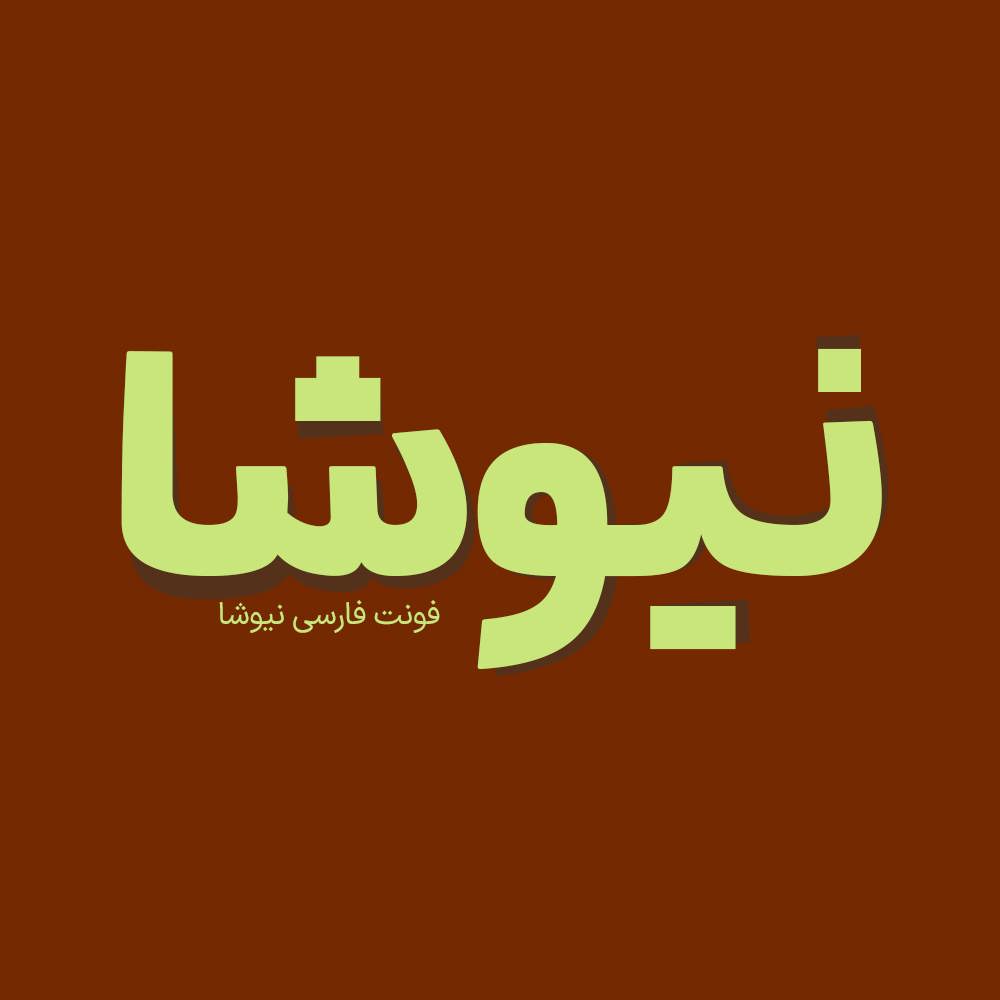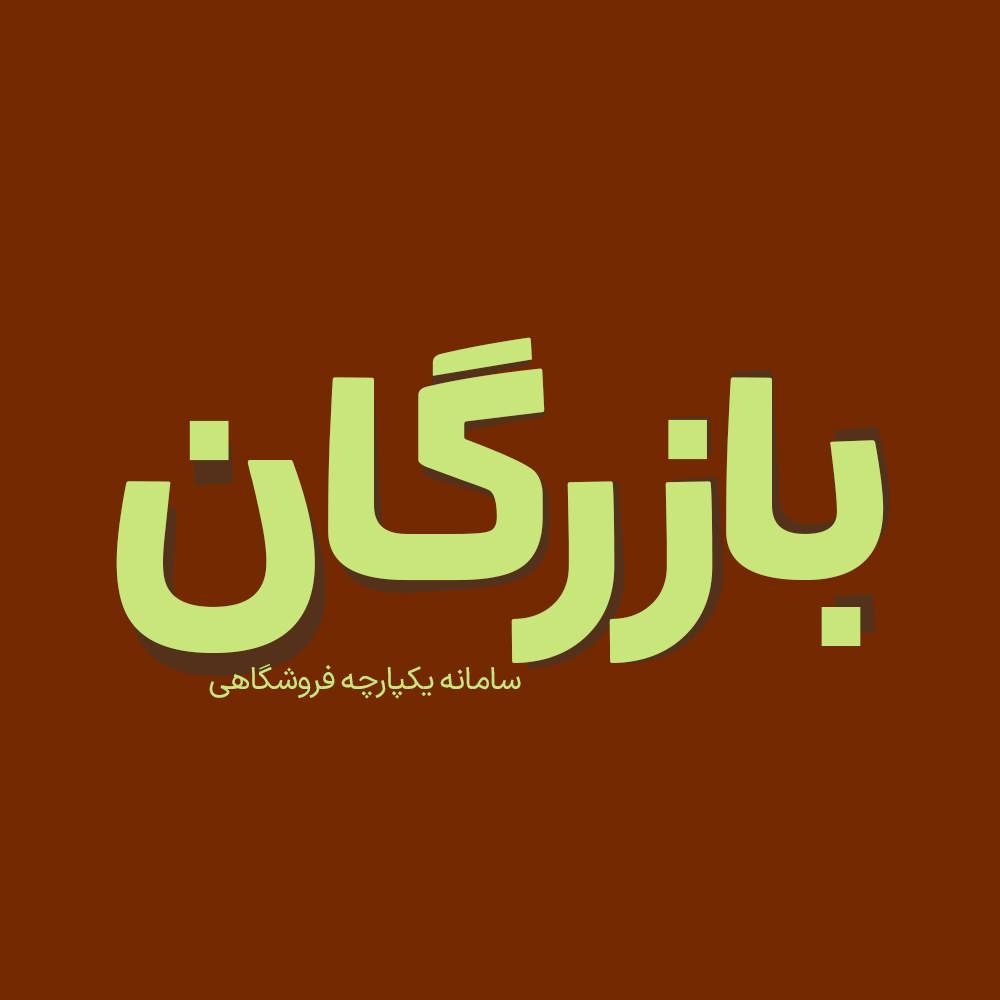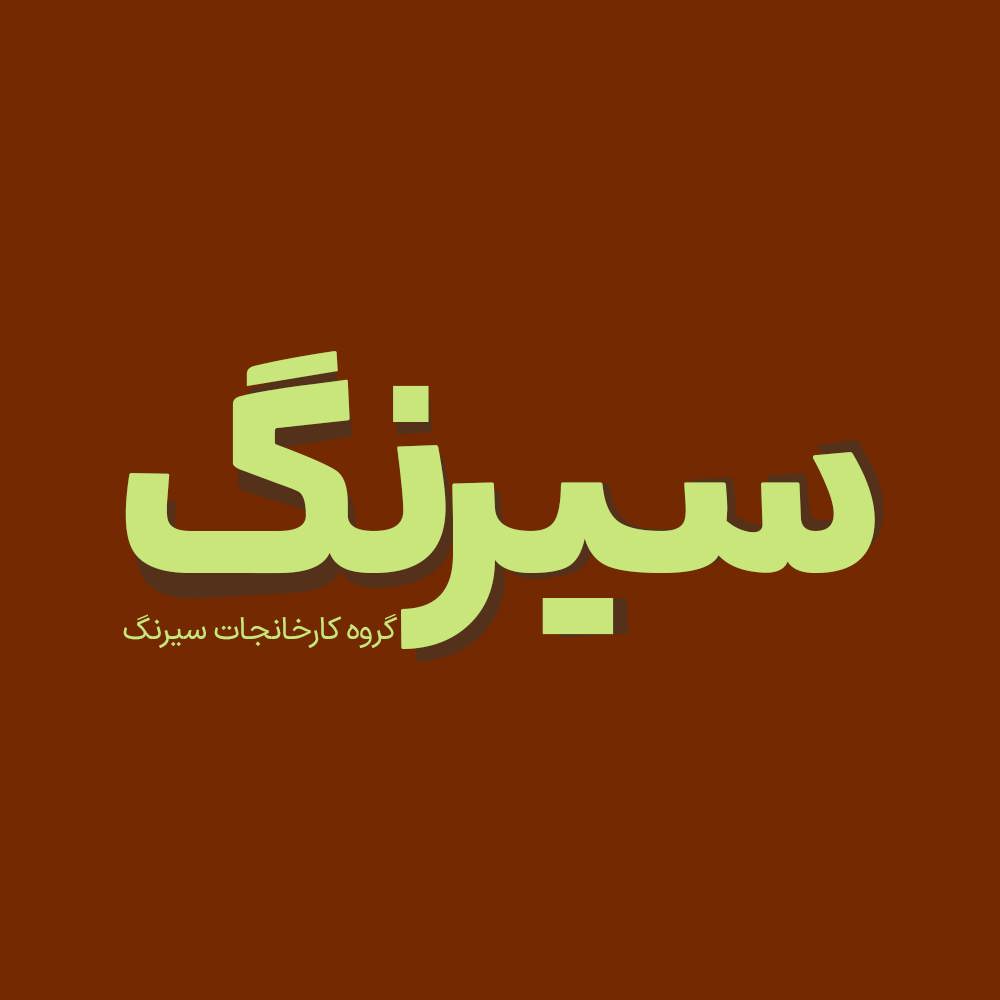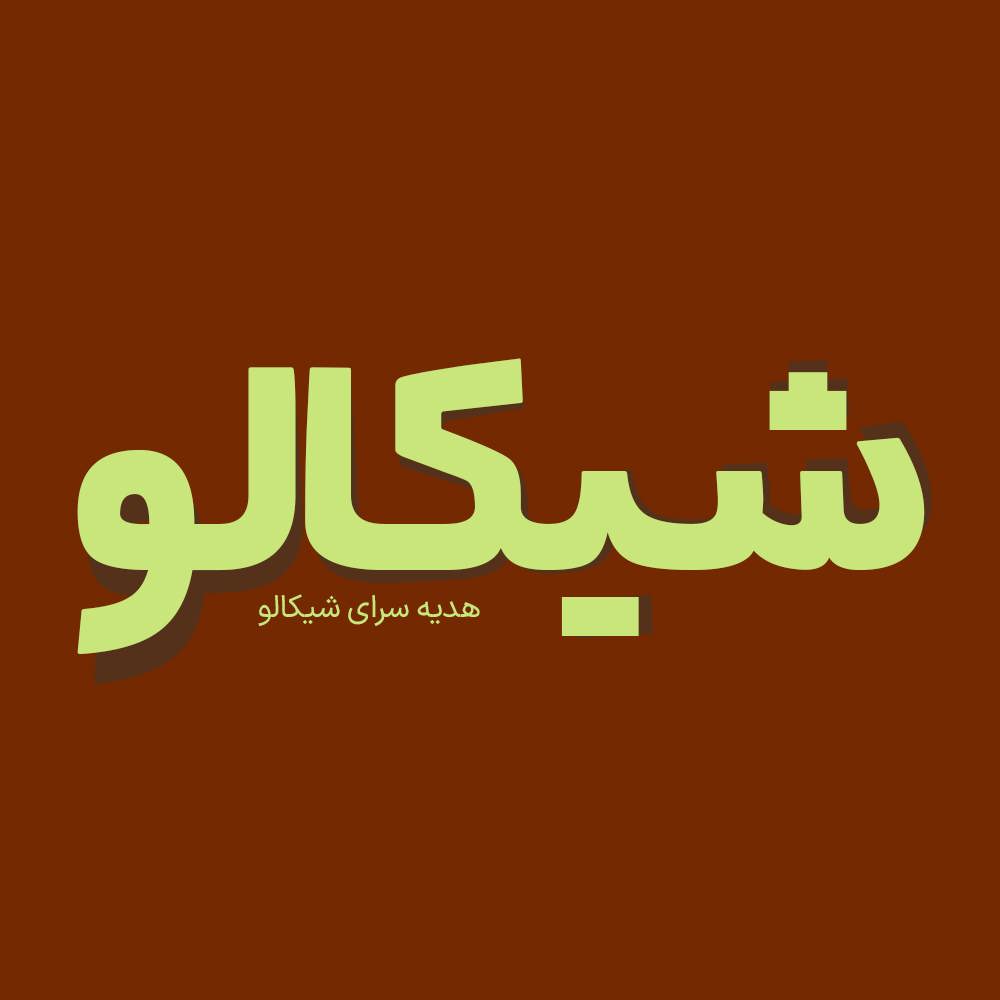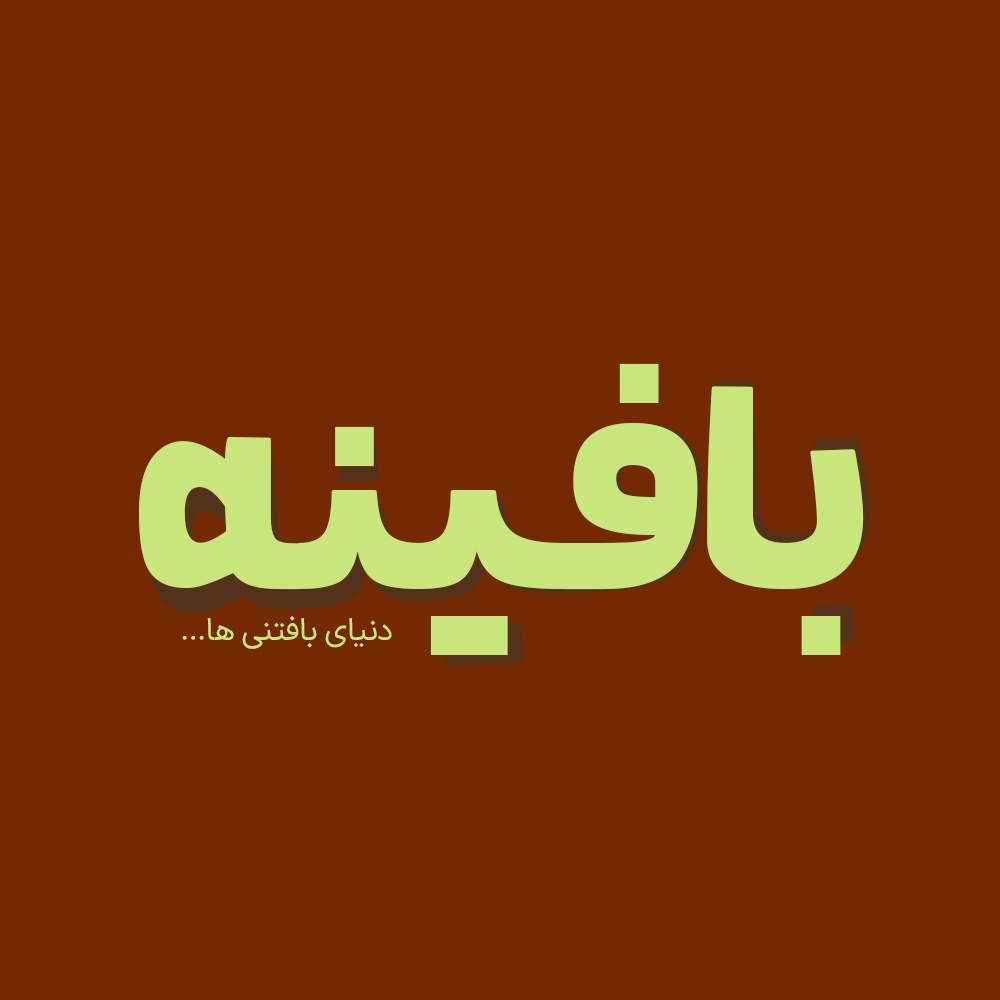
فونت فارسی نیوشا Niusha Font
فونت فارسی نیوشا یک فونت تک وزن با کاربرد طراحی لوگوتایپ و طراحی های مختلف همچون کتاب و تولید محتوای متن های کوتاه و عناوین می باشد. فونت نیوشا برای طراحی انواع امور گرافیکی به خصوص طراحی انواع لوگوتایپ و تایپوگرافی می باشد. در ادامه برای شما نمونه تایپ های این محصول حرفه ای رو آماده کردیم که میتونید مشاهده کنید.
پیشنمایش و نمونه تایپ های فونت نیوشا